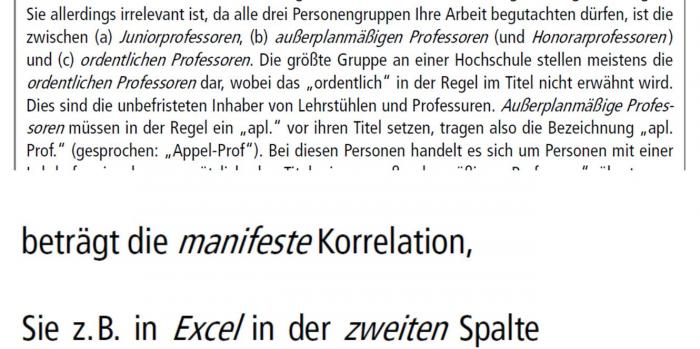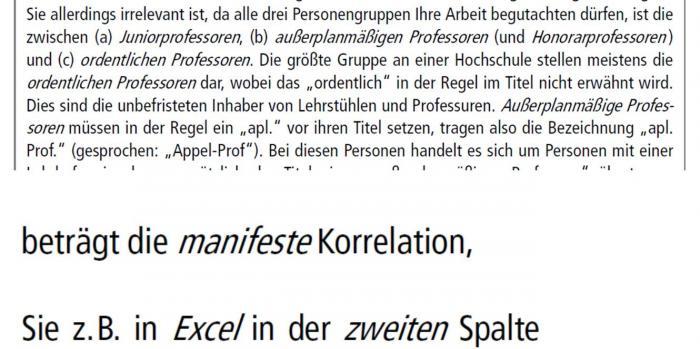
Digital kursivierte Kursive?
In den Druckfahnen eines Buches, dessen Autor ich bin, sind Exkurse in Frutiger (Condensed?) gesetzt. Innerhalb dieser Exkurse sind einzelne Wörter kursiv ausgezeichnet – man sollte meinen, mit einer Frutiger (Condensed?) Italic. Allerdings erscheinen mir diese kursiven Wörter irgendwie "extrem schräg" und ich habe die kursiv ausgezeichneten Wörter mit einer Frutiger Italic verglichen, die m.E. weniger schräg aussieht. Für mich sieht es fast so aus, als wurde eine Frutiger Italic zusätzlich digital kursiviert.
Fragen an Euch:
Wie gefallen euch die angehängten Satzbeispiele? Ich finde die nicht wirklich ästhetisch, aber ich habe gesehen, dass der Verlag auch in anderen Büchern diese starke Kursivierung gewählt hat. Bin ich da vielleicht übermäßig empfindlich? Und könnt ihr euch erklären, warum die kursiven Wörter so extrem schräg aussehen?
Was haltet ihr von der Spationierung vor und nach den kursiven Wörtern (siehe die beiden vergrößerten Ausschnitte)? Ist das so "lege artis"? (Mir erscheinen die Abstände zu dem vorherigen bzw. folgenden Wort sehr unausgewogen.)
Wie gefallen euch die angehängten Satzbeispiele? [...] Was haltet ihr von der Spationierung vor und nach den kursiven Wörtern (siehe die beiden vergrößerten Ausschnitte)?
Grausam.
Ob ich das so wohl dem Setzer zurückmelden sollte? ;-)
Wüsste gerne konkreter, was daran nicht stimmt bzw. was geändert werden soll.
Ich würd mal sagen, hier kam überhaupt keine echte Italic zum Einsatz, sondern die Frutiger Condensed wurde einfach erbarmungslos geschert. Das passiert, wenn man z.B. in Word auf den Kursiv-Button klickt, aber gar keine passende Italic installiert ist.
Ich würde das auf jeden Fall zurückmelden und mich vergewissern, dass da auch der richtige Schnitt verwendet wird.
Die echte kursive Frutiger ist jedenfalls nicht so windschief. Da wurde mit der Software (welcher?) an der Schrift manipuliert und das Ergebnis sieht hochgradig unprofessionell aus.
Ob ich das so wohl dem Setzer zurückmelden sollte? ;-)
Ich zweifle mal an, daß das ein Setzer verzapft hat. Das sieht nach Küchentisch-Verlag aus, und ja, das darfst Du so (gern wörtlich) zurückmelden.
Ich habe nur die PDF-Datei der Druckfahne. In diese sind insgesamt 14 Frutiger-Schnitte eingebettet. Vom Namen her würde am ehesten "FrutigerLTStd-Italic" passen, oder? Daneben gibt es "BoldItalic" und "LTStd-BoldItalic". (Bin mir nicht sicher, wofür "LTStd" steht.)
Eine "CnItalic" gibt es tatsächlich nicht ...
Würdet ihr denn sagen, dass es ich bei den Beispielen auf jeden Fall um eine "Condensed" handelt?
Die echte kursive Frutiger ist jedenfalls nicht so windschief. Da wurde mit der Software (welcher?) an der Schrift manipuliert und das Ergebnis sieht hochgradig unprofessionell aus.
Ich zweifle mal an, daß das ein Setzer verzapft hat. Das sieht nach Küchentisch-Verlag aus, und ja, das darfst Du so (gern wörtlich) zurückmelden.
Gesetzt wurde das in InDesign. Beim Verlag handelt es sich um ein internationales und relativ großes Haus, das v.a. Lehrbücher produziert (da sind die Auflagengrößen wenige Tausend, das ist vielleicht etwas anderes als bei populärer Literatur, mit der man auch mehr Umsatz machen kann). Der Satz wurde an eine externe Firma gegeben.
Ich habe die Neigung jetzt mal mit der normalen Frutiger Italic (allerdings nicht Condensed) verglichen und zu meiner Überraschung festgestellt, dass da offensichtlich nicht zusätzlich schräg gestellt worden ist. [Edit: Ich sollte genauer hinschauen! Da wurde doch mehr geschert als bei der echten Kursiven.] Das ändert allerdings nichts daran, dass die Wortabstände vor und hinter den kursiven Textteilen unbedingt ausgeglichen werden sollten. Wenn man die Abstände auf Höhe der Grundlinie betrachtet, sieht man, dass sie dort gleich sind. Aber weil die kursiven Buchstaben nach rechts überhängen, stehen sie oben zu dicht an den nachfolgenden geraden Zeichen und das sieht wirklich grausam aus und muss händisch korrigiert werden.
Würdet ihr dann meinen Verdacht einer gescherten Italic [ich meine eine echte Kursive, die zusätzlich geschert wurde] unterstützen? Warum tut jemand soetwas?
Sollte ein Programm wie InDesign nicht automatisch dafür sorgen, dass die Abstände vor und nach kursiven Wörtern ausgeglichen werden? Kann mir nicht vorstellen, dass man – außer in Ausnahmefällen – heutzutage bei soetwas noch händisch eingreifen muss.
Eine "CnItalic" gibt es tatsächlich nicht ...
Am Ende hat da jemand an der Schrägstellung herumgespielt und die Schrift zusätzlich gequetscht?
Würdet ihr dann meinen Verdacht einer gescherten Italic [ich meine eine echte Kursive, die zusätzlich geschert wurde] unterstützen? Warum tut jemand soetwas?
Sollte ein Programm wie InDesign nicht automatisch dafür sorgen, dass die Abstände vor und nach kursiven Wörtern ausgeglichen werden? …
Wahrscheinlich wurde ausschließlich geschert, weil oder ohne das eine echte Kursive vorhanden war. Verdachtsmoment ist der grössere Wortzwischenraum vor der Kursivierung und der kleinere nach der Kursivierung.
Gut möglich, dass diese Korrekturfahnen ohne Rücksicht auf perfekte Typografie schlicht nur zum Korrekturlesen über ein nicht so ganz kosheres PDF-Tool ausgegeben wurden, dass einen ähnlichen Fehler macht, hinterher im Bucht ist dann aber alles richtig.
Hier mal ersatzweise mit der Myriad dargestellt: oben den Grundschnitt mit 15 Grad geschert, ohne vorhandene Kursive (in die Wortabstände wurde nicht eingegriffen, die ergeben sich dann so), unten mit korrekter Italic, ohne weitere Eingriffe.